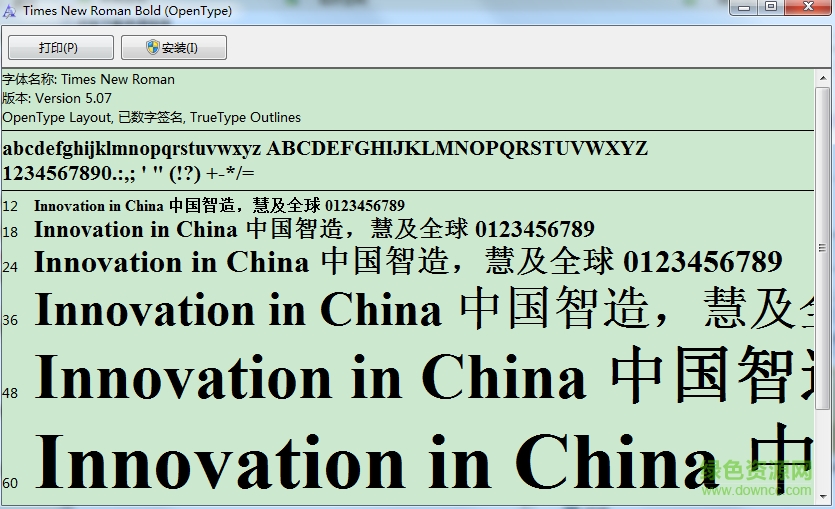
times new roman bold是一款粗體英文字體,這款字體筆畫粗壯,字形清晰美觀,線條簡約,整體效果非常出色,喜歡的話那就來綠色資源網(wǎng)下載體驗吧!
times new roman bold字體字形端正大方,表現(xiàn)力強(qiáng)!常常用于廣告設(shè)計、宣傳文本、產(chǎn)品包裝等領(lǐng)域。